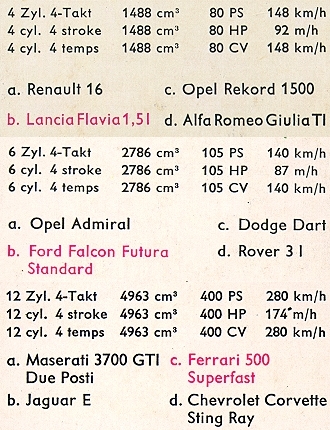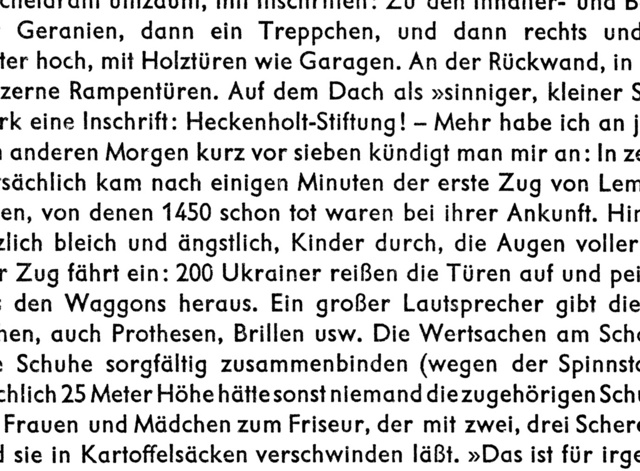
suche Schriftart Auto-Quartetts 1966 (F.X. Schmid)
Hallo, ich suche eine (gedruckte) Schriftart von Auto-Quartetts (F.X. Schmid 1966). Ich habe diverse Tools "befragt", aber nichts gefunden. Irgend etwas passt immer nicht.
Die Schrift generell deutet auf Futura/Twentieth Century hin. Jedoch stimmt das G nicht überein. Gar nicht stimmen die Zahlen. Die 1 hat keinen geraden Strich, die 4 ist offen und die 6 und 9 sind geschwungen und nicht gerade.
Vermutlich ist das für Euch kein Problem und Ihr könnt mir helfen.
Auf Typophile.com wurde das Rätsel ja auch nicht wirklich gelöst. Die Gills Infant hat ein gerades M, die Schrift in dem Typophile-Muster auch ein schräges. Der Gesamteindruck kommt der Gill schon am nächsten, mit der Diagnose Gill-Modifikation liegt man bestimmt nicht falsch, bleibt nur die Frage, ob es noch eine präzisere Antwort gibt.
Die Gill Sans des Ostens kann es ja eigentlich auch nicht sein, oder? Wie hieß die gleich noch mal? Hab’ gerade kein Bild vor Augen, nur so ein fixer Gedanke. :-?
Das ist doch eine echte Standardschrift! „Metro“ von William Addison Dwiggins (1936)
Es gibt aber verschiedene Versionen, die hier gezeigte 4 ist so in den neuen Digitalisierungen selten bis gar nicht anzutreffen. Die scheint noch aus den alten Originalversionen zu kommen. Guckst Du hier:
Dieses Schicksal erlitt auch die 4 in der schmal-leichten Erbar. :cry:
Einen Klon der Metro gibt es als Geometric 415 in der Bitstream-Sammlung die mit vielen Corel-Produkten ausgeliefert wird. Die Examiner NF ist eine weiterer Neuinterpretation. Ich habe eine Metro täglich vor Augen, nur wenige Meter von meiner Haustür weg. :!:
Jedoch passt auch die "MetroLight Two" Schrift nicht genau.
Das "G" ist 100% richtig (hatte ich so noch nicht gefunden), ebenso pssen "M" und "a". Jedoch hat das "t" bei "MetroLight Two" unten einen Bogen und das "u" ist unten nicht "nur" rund.
Außerdem ist die "1" oben einfach nur gerade, die "4" ist wie von Dir bemerkt nicht richtig und auch die "6" und "9" sind im Strich zu gerade:
Gibt es noch irgendwelche andere Arten der Metro Schrift, die vielleicht noch besser passen könnten?
Jedoch passt auch die "MetroLight Two" Schrift nicht genau. Das "G" ist 100% richtig (hatte ich so noch nicht gefunden), ebenso passen "M" und "a". Jedoch hat das "t" bei "MetroLight Two" unten einen Bogen und das "u" ist unten nicht "nur" rund. Außerdem ist die "1" oben einfach nur gerade, die "4" ist wie von Dir bemerkt nicht richtig und auch die "6" und "9" sind im Strich zu gerade:
Gibt es noch irgendwelche andere Arten der Metro Schrift, die vielleicht noch besser passen könnten?
Ich habe dieses Bild mit den Buchstaben einfach http://www.whatfontis.com/ zum Fraß vorgeworfen. Raus kommen gleich zuerst: Die Geometric 415 BT, Metro, GPMetro und DH-Sans, also die üblichen Verdächtigen. Das könntest Du mal mit diesen Buchstaben aus einem sehr hochaufgelösten Scan einer der Karten machen und schaun was raus kommt.
Das Original ist vielleicht eine modifizierte Metro als Bleisatzschrift, welche aber sehr wahrscheinlich nicht digitalisiert wurden. Die Buchstaben in der Form des Original kennt man aber aus anderen Grotesk-Schriften der 1920er, jenseits der Futura. Aber in groben Zügen sollte man die Schrift so beschreiben können: Eine Metro mit modifizierten Buchstaben, typisch für die geometrischen Grotesk der 1920er aus Deutschland?
habe wohl das gleiche Problem mit derselben Schrift. „Meine“ stammt aus einem bleigesetzten Bertelsmann-Buch von 1961. „whatthefont“ macht komische Vorschläge dazu: Volkswagen, Richmond, Carnova, Futura SH. In Bleisatz-Schriftmustern finde ich nichts und die Metro-Lösung ist auch ziemlich weit weg.
Eigentlich ist es ja wurscht, weil diesen Font wahrscheinlich nicht digitalisiert gibt. Aber das Jagdfieber …
Hoffe, dass es hier noch weiter geht.